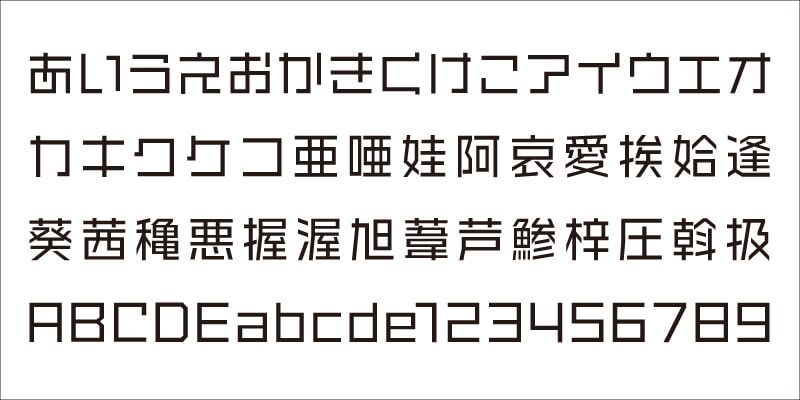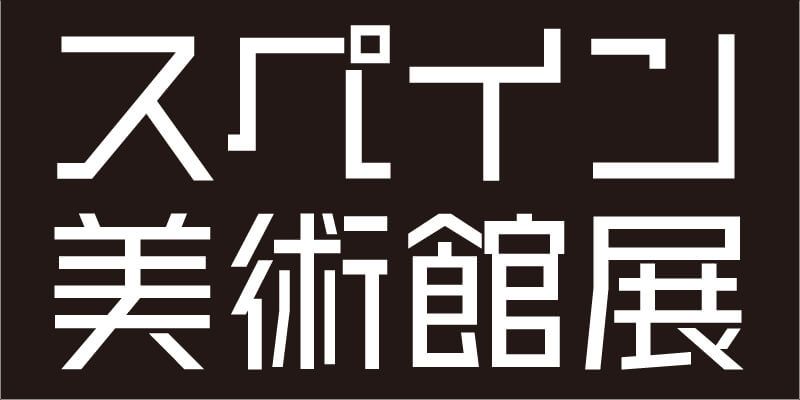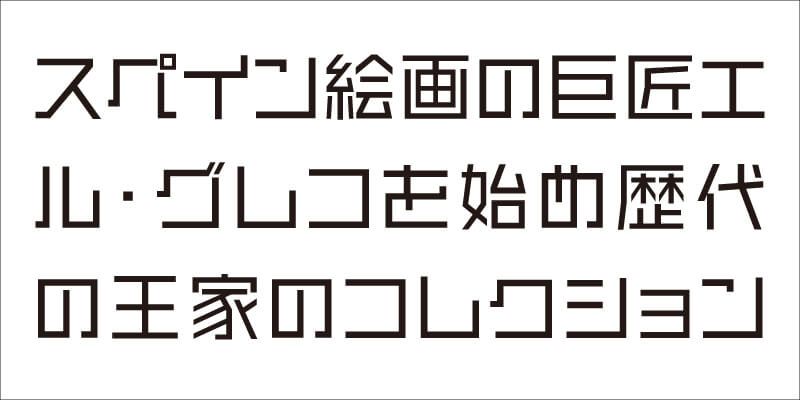
Se trata de un tipo de letra gótico (sans-serif) muy elaborado. Todos los caracteres se componen de líneas rectas, y los elementos curvos se eliminan por completo sin dejar de ser legibles. El diseño es muy sencillo, con una apariencia nítida y fuerte que estimula la curiosidad del espectador.
Visual Design Laboratory (VDL) cree en equilibrar la belleza natural de las formas de las letras con estándares rigurosos de legibilidad. VDL ofrece una completa colección llamada “VDL Designers Fonts” (VDLデザイナーズフォント), que seguro va a resonar con diseñadores que buscan un tipo de letra muy individual manteniendo un gran atractivo.